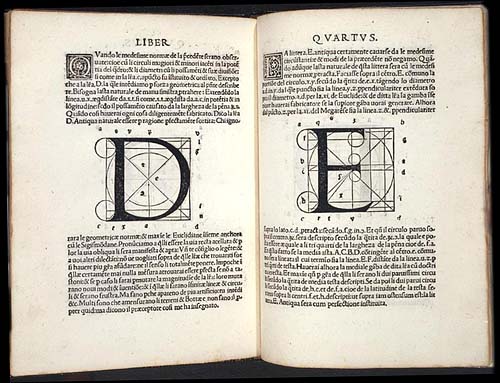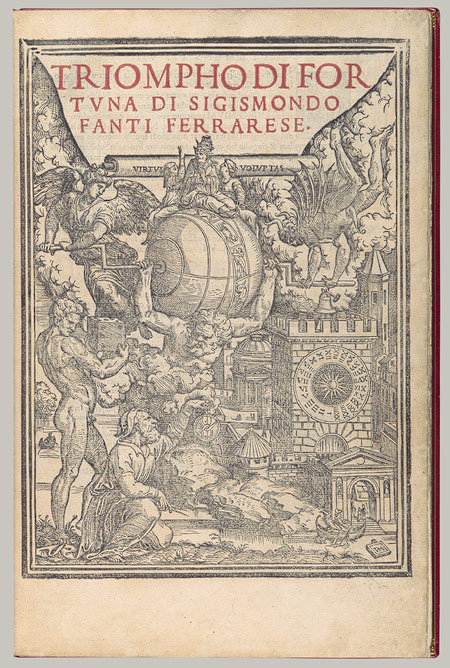
Sigismondo FantiTratadista das ciências e artes da Renascença italiana. Matemático e astrónomo, oriundo de Ferrara.Com Sigismondo (ou Sigismundo) Fanti, os trabalhos dos mestres calígrafos italianos começam a ter influências directas na ainda jovem tipografia. O matemático Fanti foi o autor de uma importante obra pedagógica sobre tipografia e composição: Liber elementorum Theorica et pratica [...] de modo scribendi fabricandique omnes litterarum species, livro impresso em 1514 por Giovanni de Rubeo (ou Rosso), em Veneza.
Nesta obra, dividida em quatro livros, Fanti tratou não só a Capitalis romana, mas também outras letras; infelizmente, não conhecemos exemplares das letras cursivas. TornielloFrancesco Torniello publicou em 1517 uma Opera del modo de fare le littere maiuscole antique, com mesura de circino & resone de penna. Contrariamente aos seus antecessores, Torniello mostra na sua obra construções já bem claras e precisas, desenhos sem quaisquer ambiguidades geométricas. Com a influência da Operina de 1522, obra de Ludovico Vincentino degli Arrighi, um calígrafo de Veneza, as formas caligráficas dos mestres escritores italianos começam a fazer-se perceber em certos tipos de chumbo, especialmente nos tipos itálicos. O tratadista Giovanni Tagliente, que publicou em 1524, deu pouco valor às versais e preferiu ocupar-se em pormenor das letras cursivas. Ugo da Carpi repetiu em detalhe as formas das inscrições da Antiguidade no seu Thesauro de Scrittori, obra publicada em 1535. Em 1527, Giovan Battista Verini pôs novamente as versais em correlação com o corpo humano, mas também com as leis da arquitectura clássica postuladas por Marcus Vitru vius Pollio.